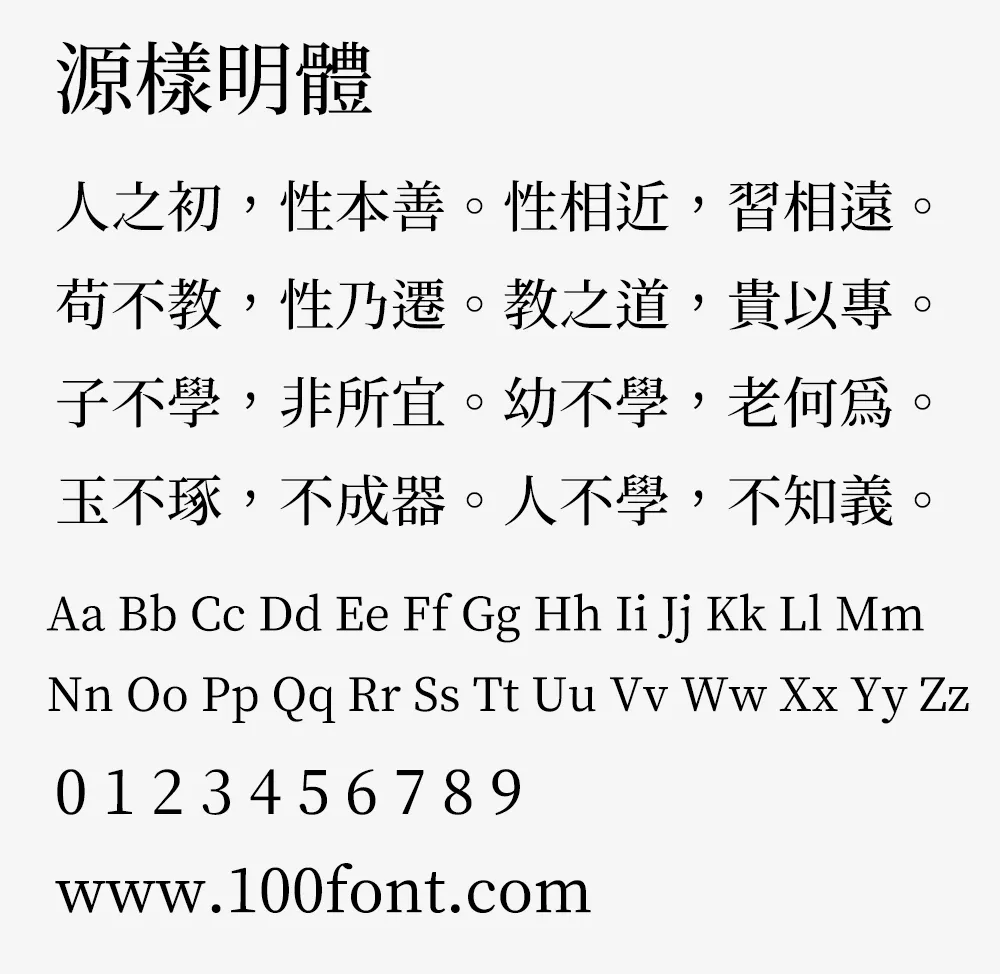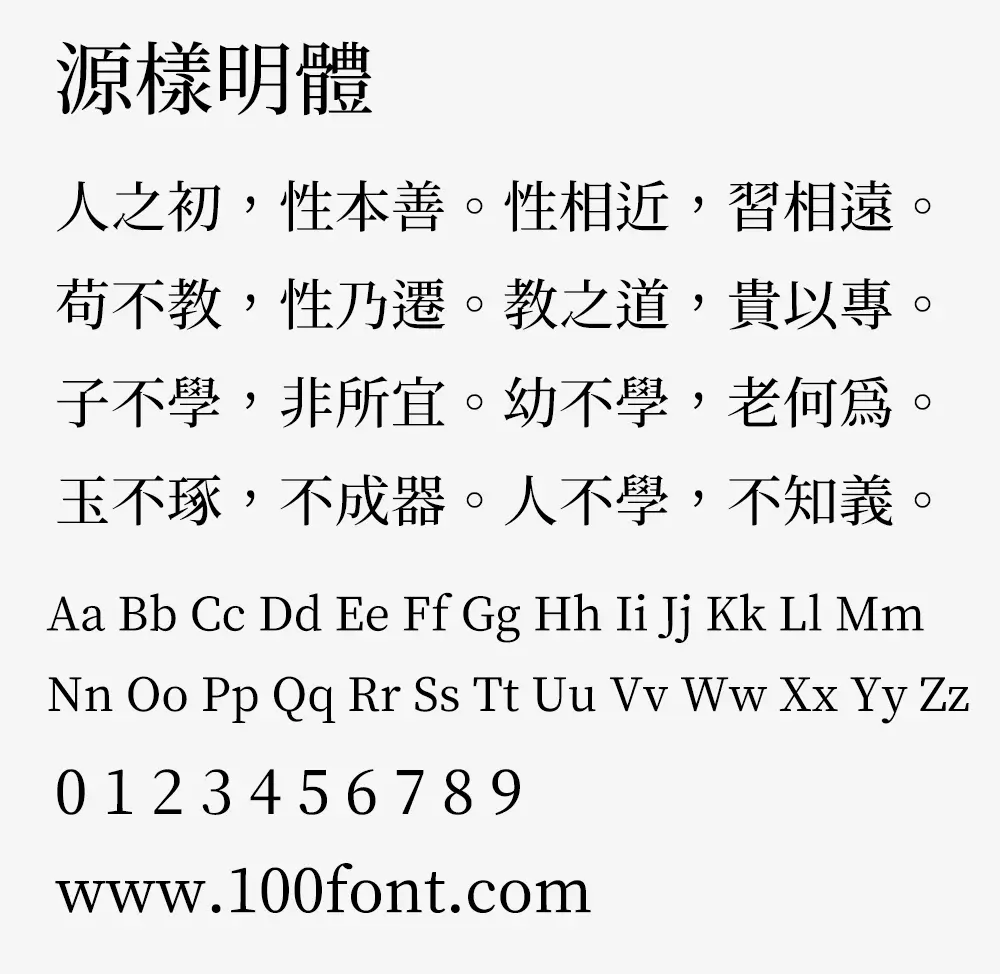
源樣明體是一種傳統印刷體風格且易用的繁體中文字型,由臺灣字型社團「字嗨」管理員 But Ko基於“思源宋體”修改衍生而來,字體改造雖以計算機程序自動進行,但在一些細節調整後可以明顯感受出不同效果,源樣明體採用思源宋體韓文版本的字符,配合繁體中文習慣的置中標點符號,可說是兼具排版及傳統印刷體風格的繁體中文字體
注意提醒:這款字體主要適用於繁體,雖然簡體中文也支持,但是簡體可能會出現錯別字等情況。